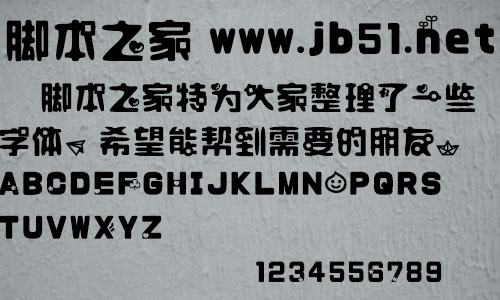
字體管家哆啦A夢(mèng)是一款不錯(cuò)的藝術(shù)字體,由Aa字庫(kù)出品,字體筆觸粗實(shí),字形端正,點(diǎn)綴了一些哆啦A夢(mèng)的卡通元素,適合應(yīng)用于藝術(shù)設(shè)計(jì)、平面宣傳設(shè)計(jì)、網(wǎng)頁(yè)設(shè)計(jì),書(shū)法字帖等領(lǐng)域,需要的朋友可以前來(lái)本站下載。